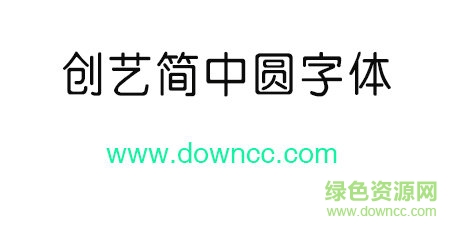
ctzhongyuansj
ctzhongyuansj字体就是创艺简中圆字体,该字体笔触细腻,字形简洁优雅,十分美观,让你在创作文章时都会有一项更好的字体选择,而且还是可以永久免费使用的哦。你可千万别错过了,喜欢的小伙伴快来绿色资源网下载收藏吧!
ctzhongyuansj字体特点
创艺简中圆是一款简单、大方的简体广告字体,创艺简细圆字体笔画均衡,折角处圆润没有棱角。如果你想将其用于商业用途,则需要联系作者取得授权。
笔画适中,造型秀美适意,笔画流畅,点画呼应,用在很小的字号时仍具有清晰、明快的阅读效果~!